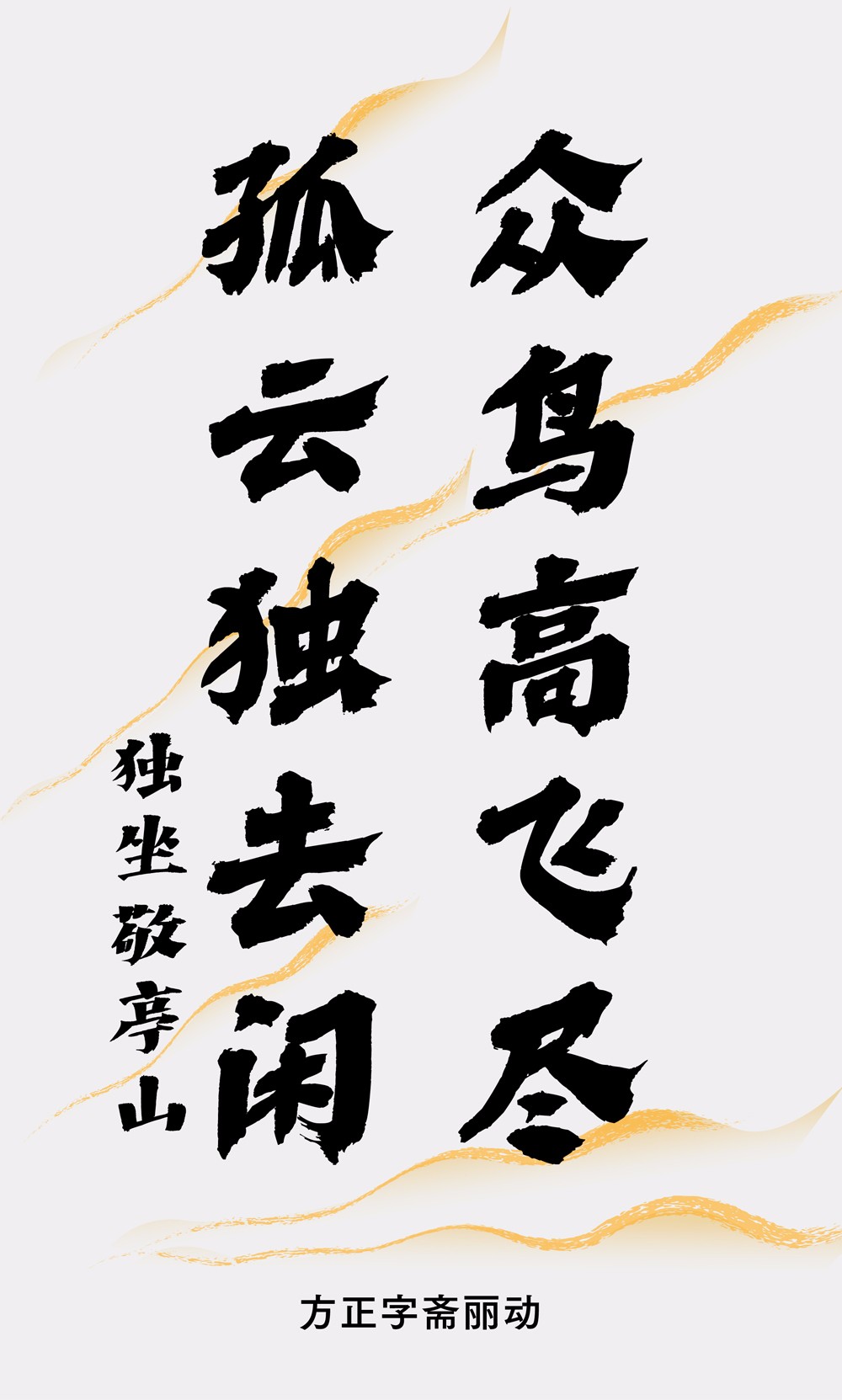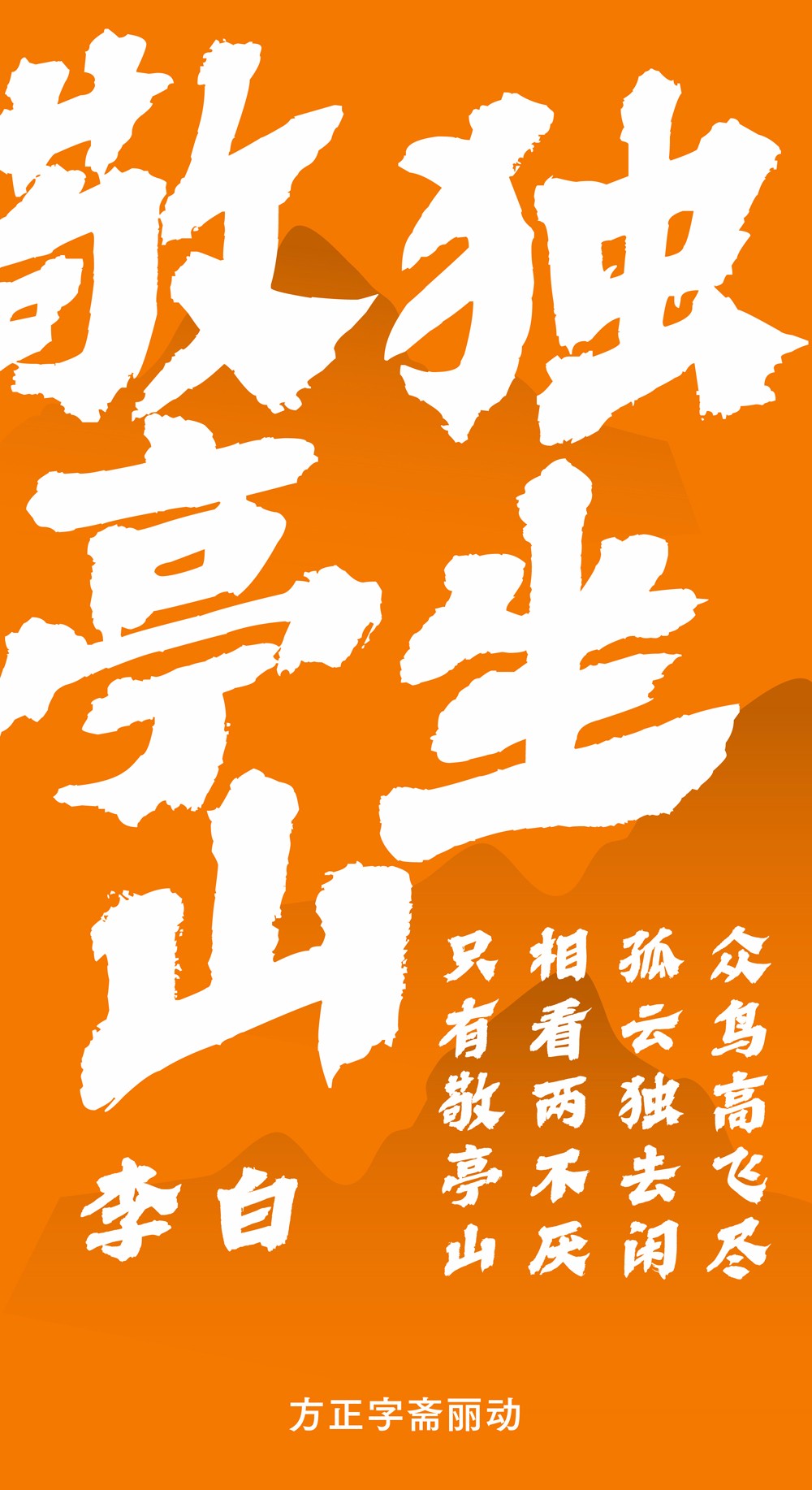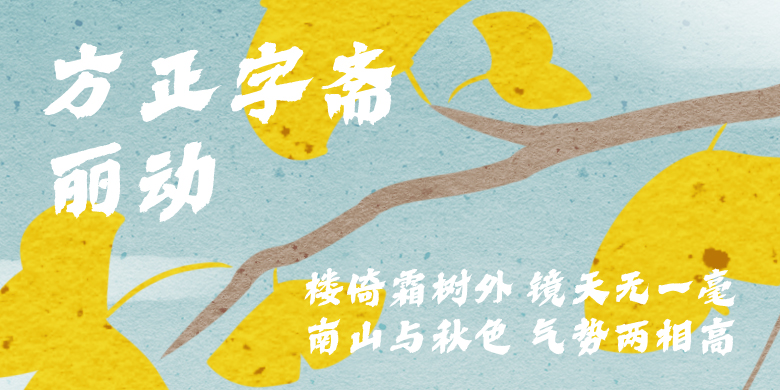
方正字斋丽动
方正字斋丽动,这款字体结构工整、笔画清晰,兼顾美观与易读性,适用于标题、正文、海报、包装、LOGO 等多种场景。字形优雅稳定,风格百搭耐看,适配日常排版与创意设计,让文字呈现更舒适、更具质感。方正字斋丽动一笔一画,皆是细节,以均衡的比例、流畅的线条打造舒适视觉体验,字形端正大气,风格简约现代。无论是商业设计、品牌宣传还是日常排版,都能轻松驾驭,让文字更有格调与力量。方正字斋丽动字体下载。
如果说市面上的楷书饱和或太多了,那隶书相对少了很多,可选择性也小,且给人横平竖直的传统印象。艺术大师达•芬奇说,预赋静止以生命,必先使其有动感。就字的外形面貌而言,动感不是美术字体的专属。动感隶书今天有的一见。为探索其可能性,赋予隶书以动感,而且一反常规的老态龙钟印象,难度相当大。
《方正字斋丽动》是一款有动感隶书风格的字,与传统相比,这款字青年有活力,给人积极的一面。字重偏粗,适合做标题,横竖结宜,简单排版绰绰有余,整体质量基本稳定。字体通过载体传递力量,需要我们不断努力纵挖,尝试更多可能性。